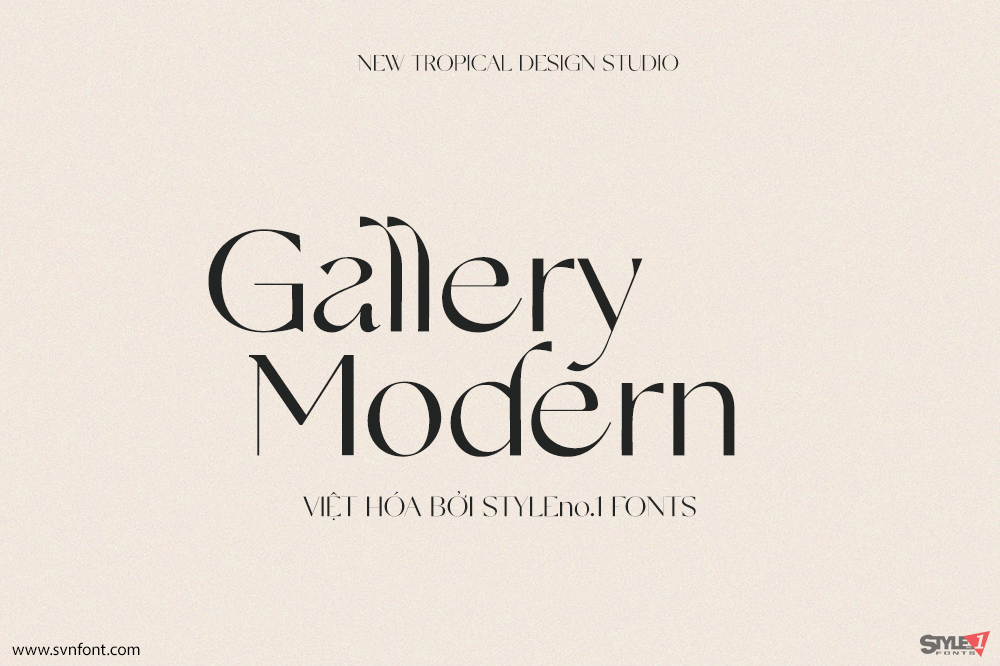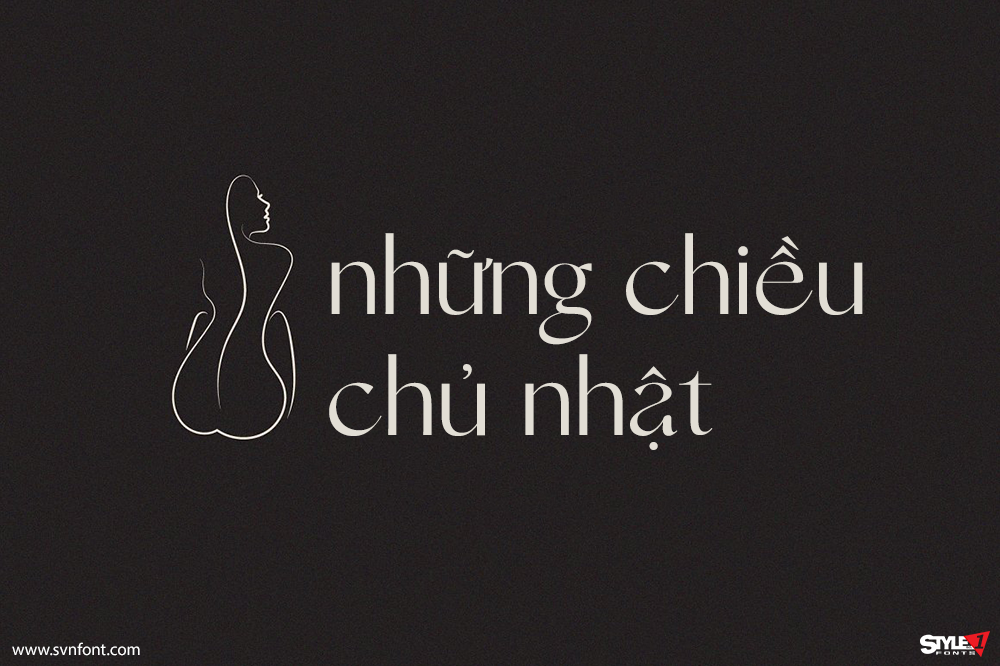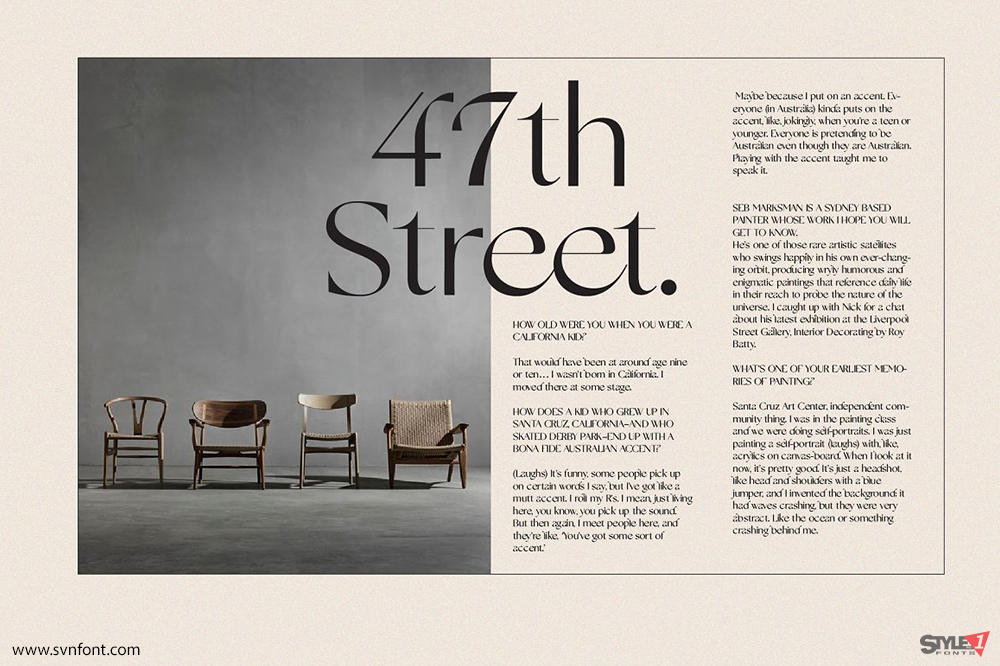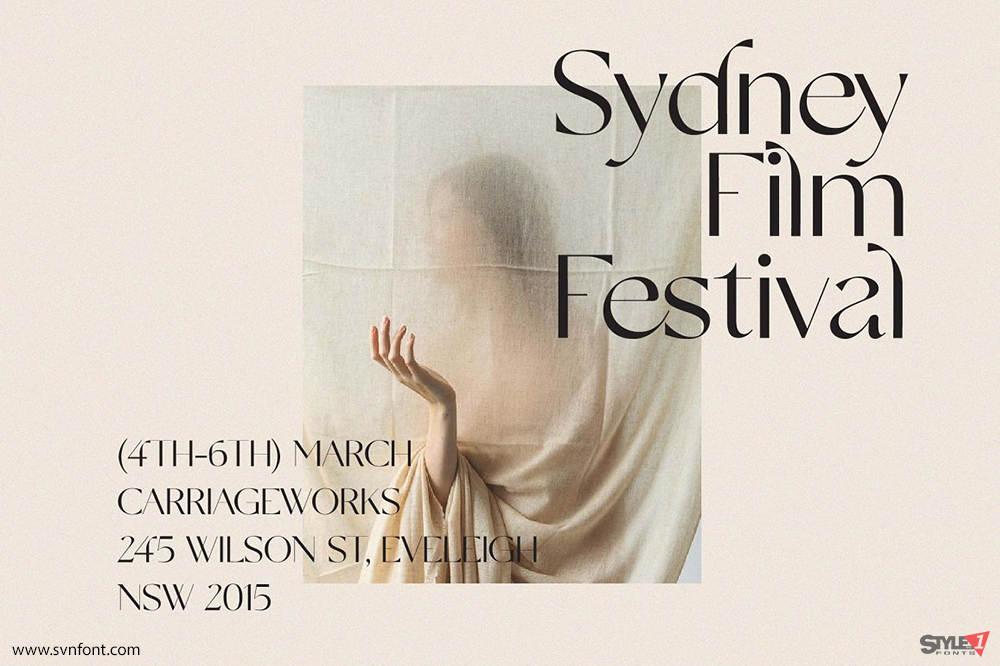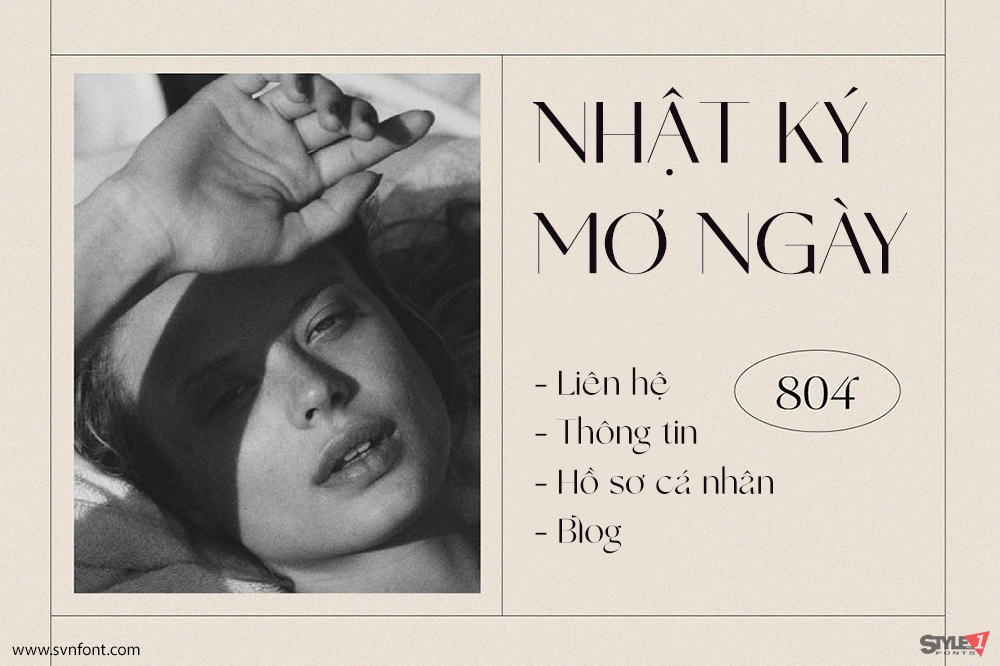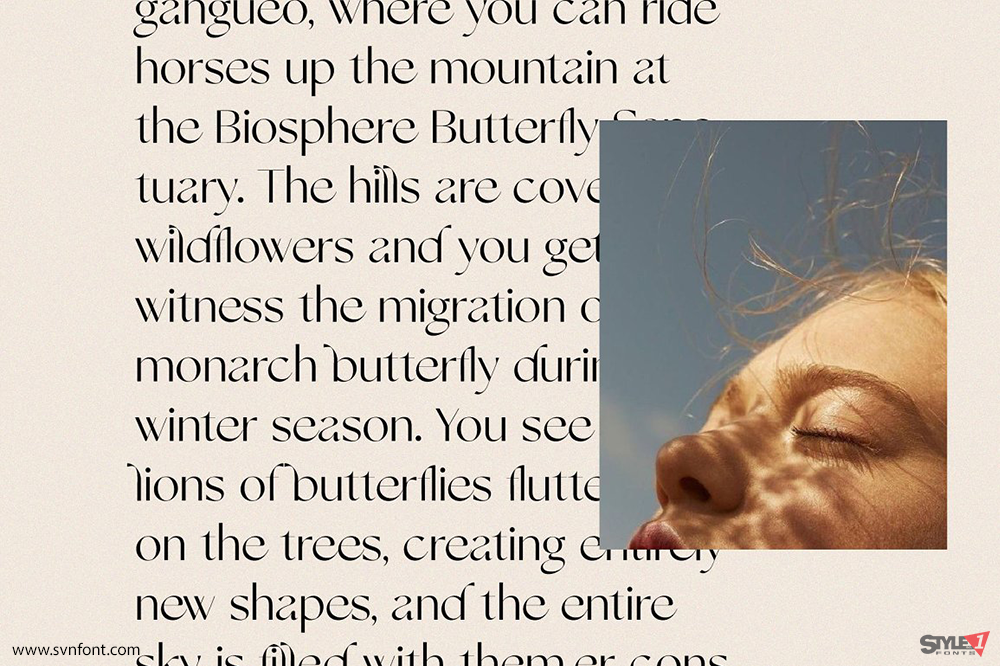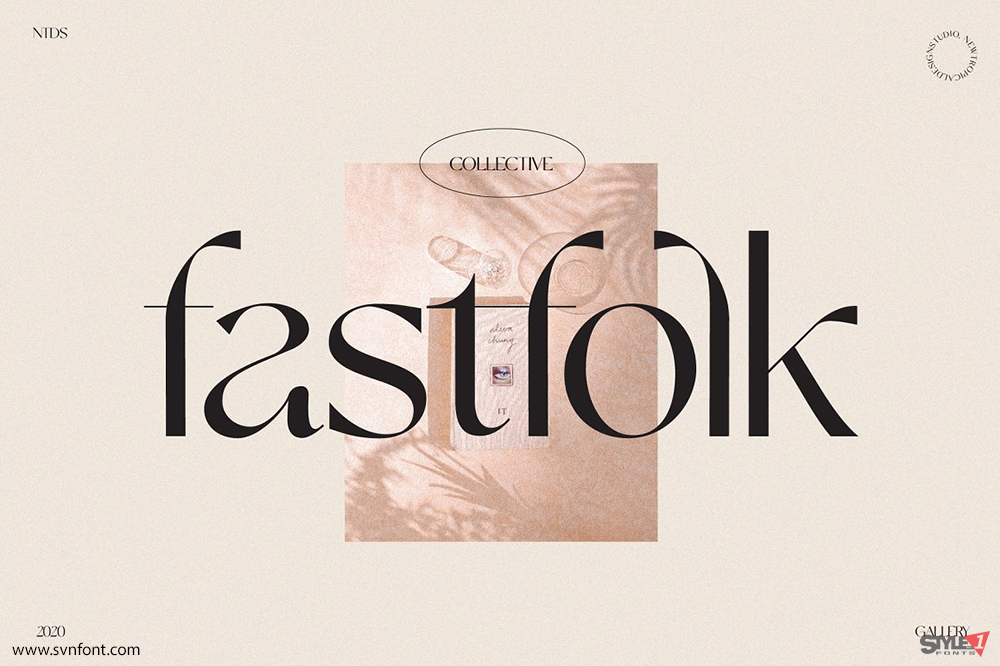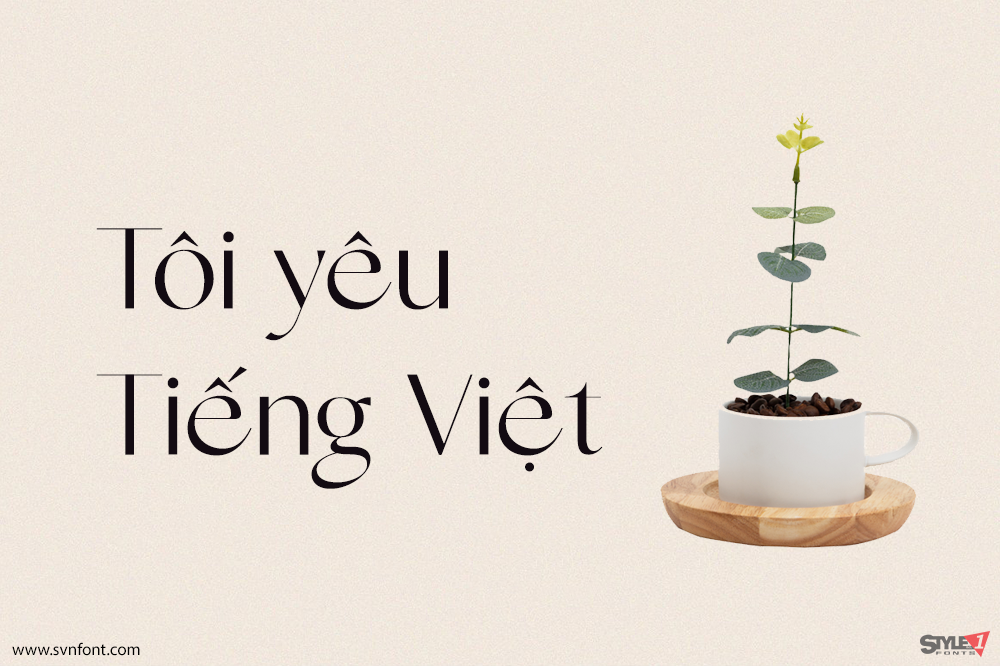
Gallery Modern là một font chữ hiện đại, vừa dễ ghi nhớ vừa mang phong cách thời trang. Những đường cong mượt mà của chữ “a” và các nét thân cong của những chữ có phần vươn cao tạo nên một font chữ độc đáo. Đây là sự pha trộn giữa serif cổ điển và sans serif mang hơi hướng tương lai. Gallery đi kèm đầy đủ chữ hoa, chữ thường, chữ số và dấu câu, đồng thời hỗ trợ các ngôn ngữ châu Âu. Font chữ này rất phù hợp cho branding thời trang hoặc thiết kế biên tập, thể hiện hài hòa cả nét nam tính lẫn nữ tính.